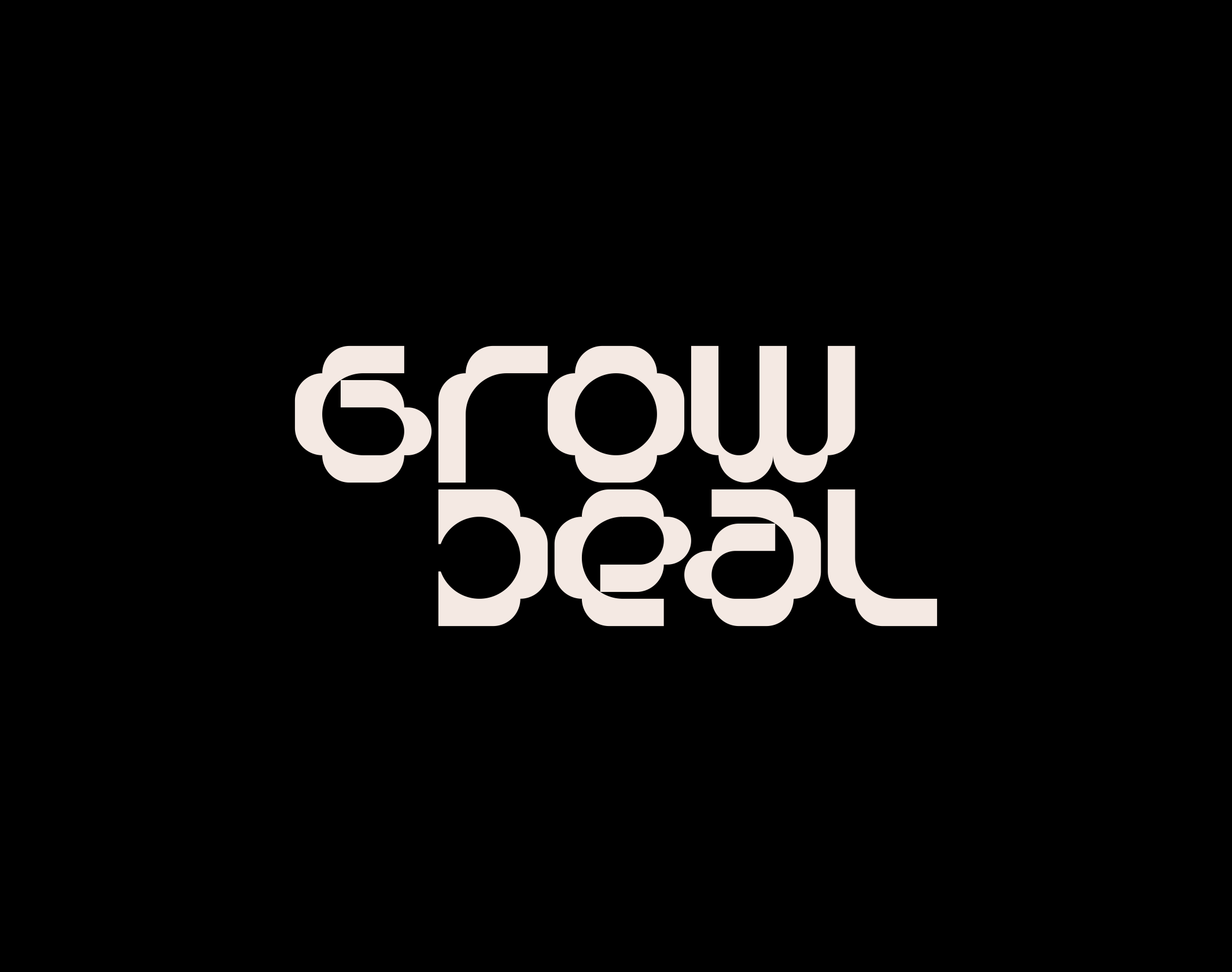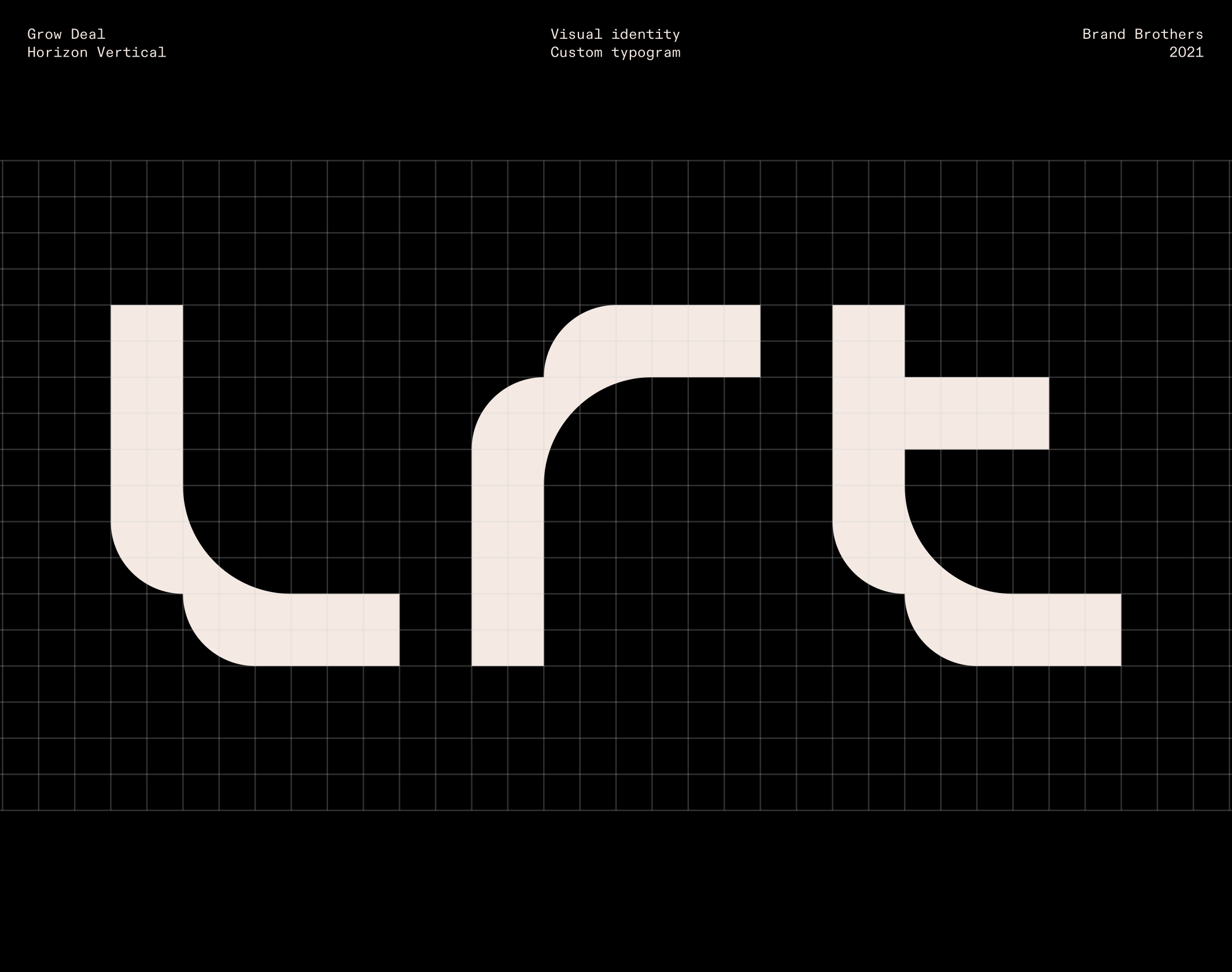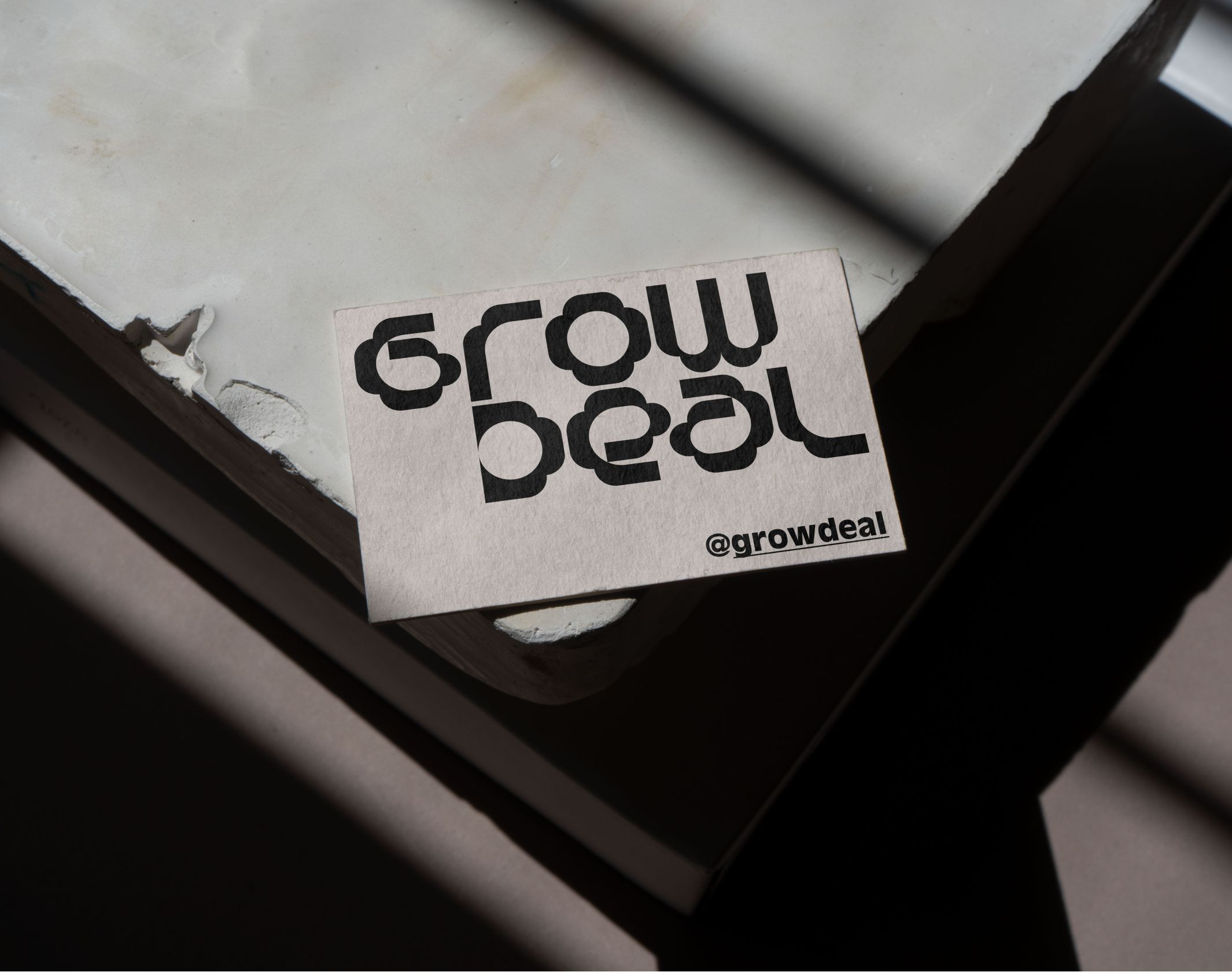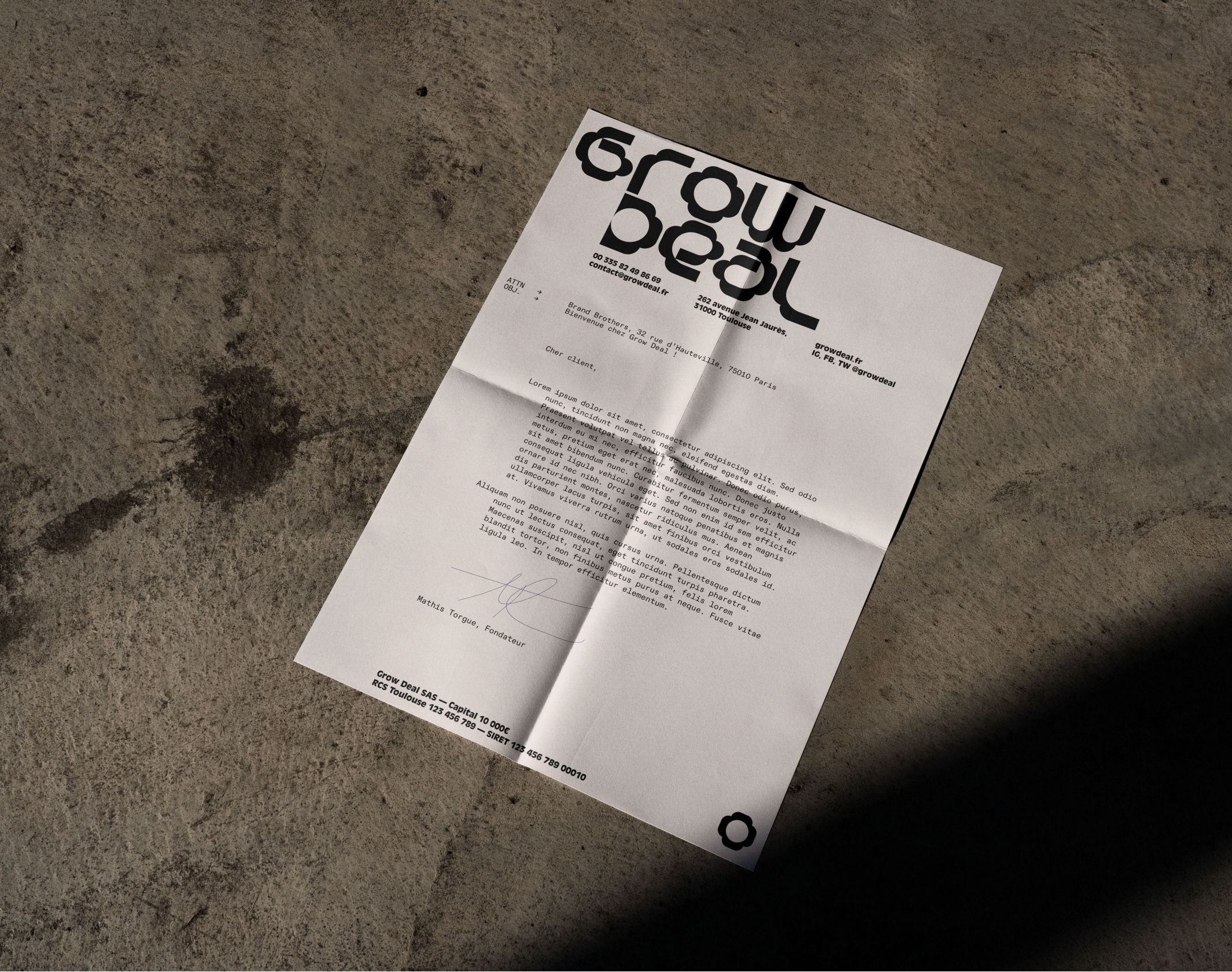
Grow Deal
Brand Brothers a redéfini l'identité visuelle de Grow Deal, pionnière de l'agriculture verticale à Toulouse, avec un design innovant et percutant.
Grow Deal est la première ferme verticale de Toulouse, située au coeur du Marché d’Intérêt National de la ville. Il s’agit de la première ferme verticale d’intérieur de France à cultiver directement sur place, et gère également une seconde ferme dans le sous-sol et sur le toit d’un supermarché toulousain. Grow Deal y cultive des champignons, des aromates rares, de fleurs comestibles et de micro-végétaux sous la marque Horizon Vertical ; ils sont livrés le jour de la récolte et cela toute l’année, dans un environnement de culture strict.
Brand Brothers a accompagné le fondateur de Grow Deal dans la refonte complète de son identité visuelle. Nous avons opté pour un système graphique et typographique fort, hors des codes habituels des secteurs alimentaires et végétaux. Le typogramme, conçu au studio, reprend une structure géométrique stricte et des courbes qui forment des excroissances, rappelant le bourgeonnement des plantes. Sur cette base, un système de formes vient enrichir la grammaire visuelle et forme la base des applications graphiques, qui se déploient dans des environnements aussi variés que des étiquettes monochromes, du textile ou sur les réseaux sociaux. De nombreuses nouvelles déclinaisons à venir.